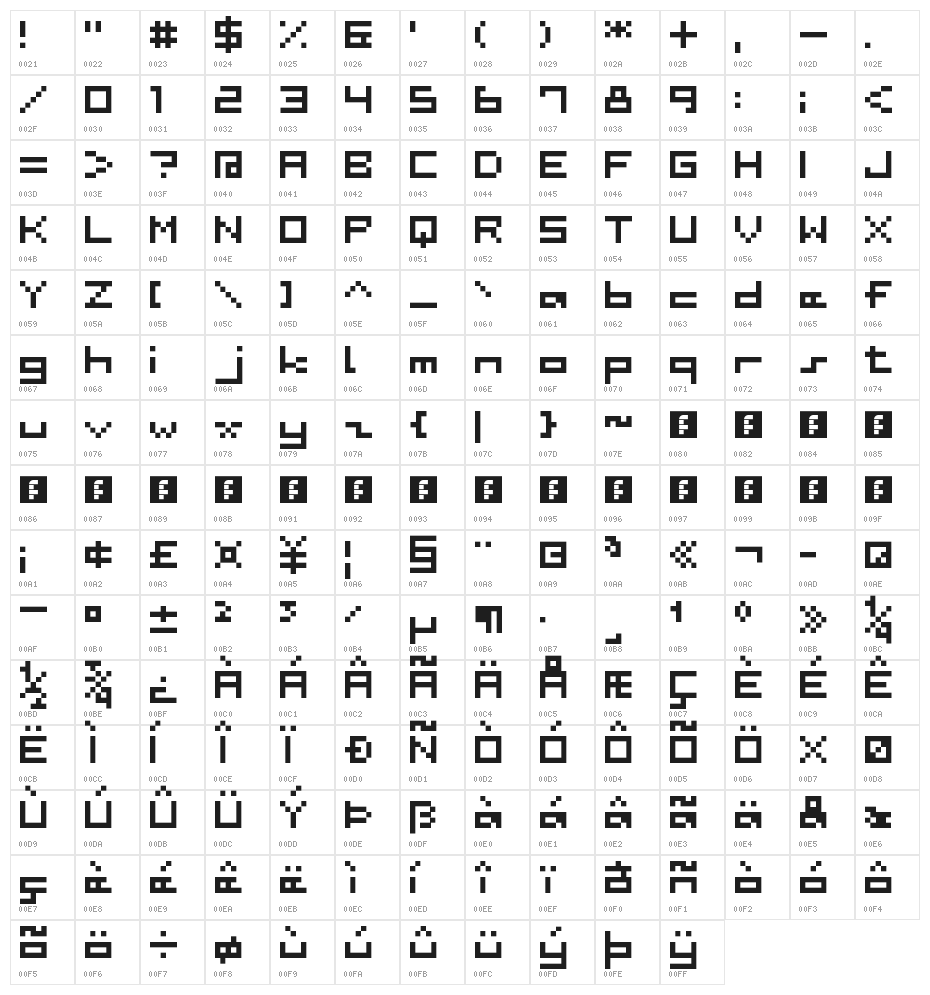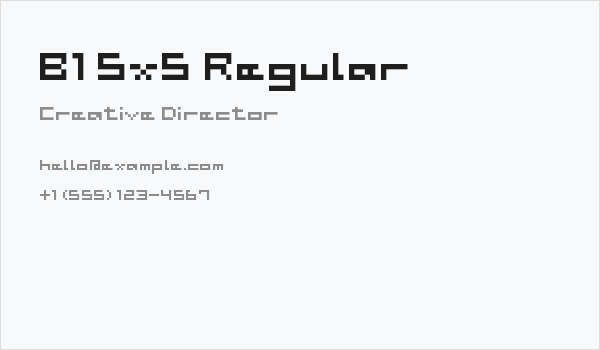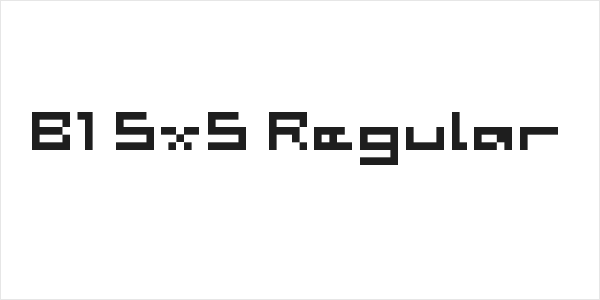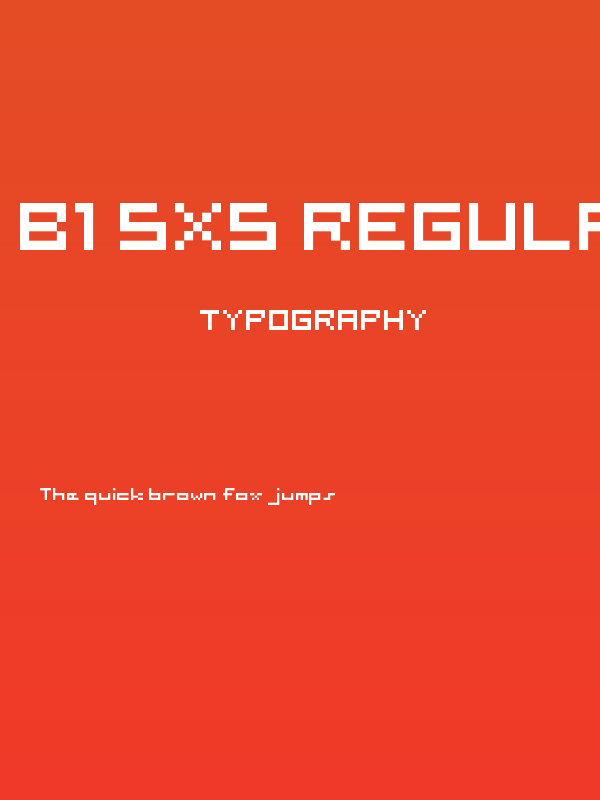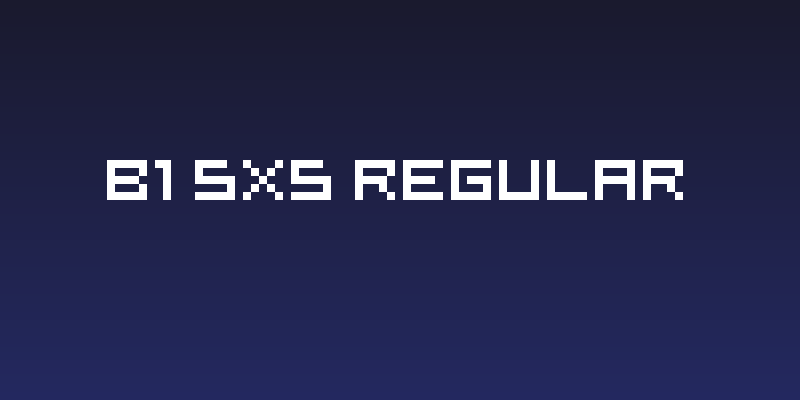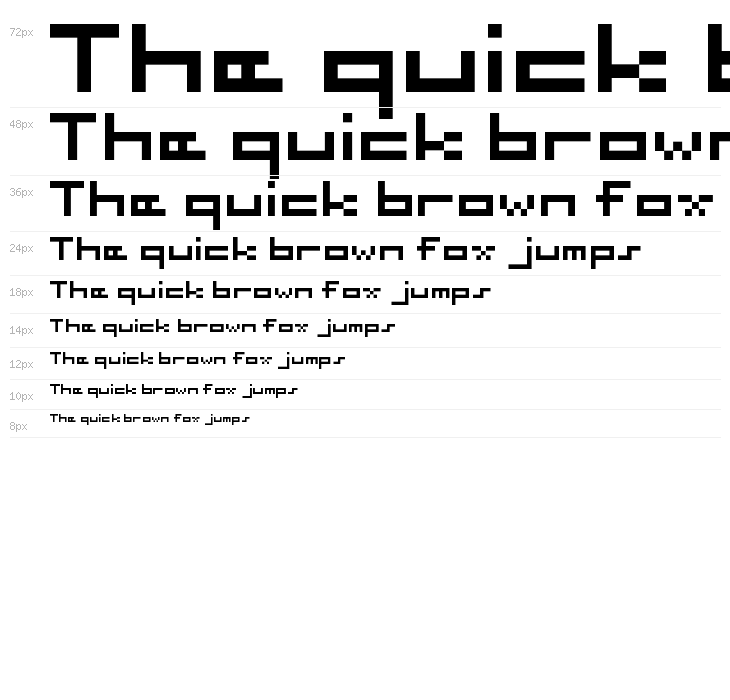
B1 5x5 Regular Font
✎ Pixel
| Caso d'uso | Logos, Headlines, Digital Art |
| Progetti proposti | Ideal for retro-themed designs, video game graphics, digital art projects, and any creative work that seeks to evoke a sense of nostalgia for early computing. |